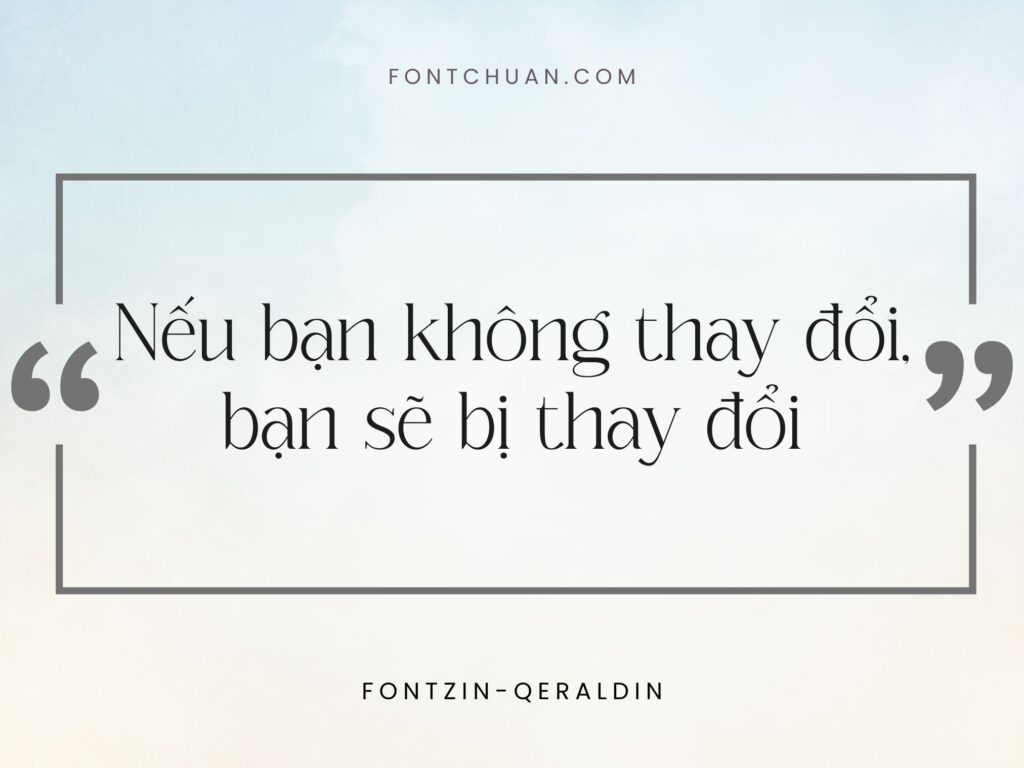
Font Fz-Qeraldin Việt Hóa
Tác giả Font: Letterena Studios
Việt hóa bởi: Fonttiengviet
Fz Qeraldin là một phông chữ serif hiện đại, được thiết kế bởi Letterena Studios. Phông chữ này mang phong cách thanh lịch và cổ điển, với các đường nét mềm mại và chân chữ sắc nét, tạo nên vẻ đẹp sang trọng và chuyên nghiệp. Phiên bản Fz Qeraldin đã được Việt hóa bởi Font Zin, hỗ trợ đầy đủ các ký tự tiếng Việt, giúp người dùng dễ dàng ứng dụng vào các thiết kế mang bản sắc địa phương
Với thiết kế tinh tế và hài hòa, Fz Qeraldin vừa là một Font Display lý tưởng cho các tiêu đề, bìa sách, logo và ấn phẩm cần sự nổi bật, vừa có thể được sử dụng như một Font chữ thiệp cưới sang trọng, mang đến vẻ đẹp trang nhã và lãng mạn cho các thiết kế thiệp cưới, thiệp mời hoặc các ấn phẩm liên quan đến sự kiện đặc biệt. Font này phù hợp cho các ứng dụng như thiết kế logo, tiêu đề, bìa sách, bao bì sản phẩm và các dự án sáng tạo khác. Về ngành nghề, Fz Qeraldin đặc biệt phù hợp với lĩnh vực quảng cáo, giáo dục, thiệp cưới và ảnh cưới, giúp nâng tầm tính chuyên nghiệp và thẩm mỹ trong thiết kế.